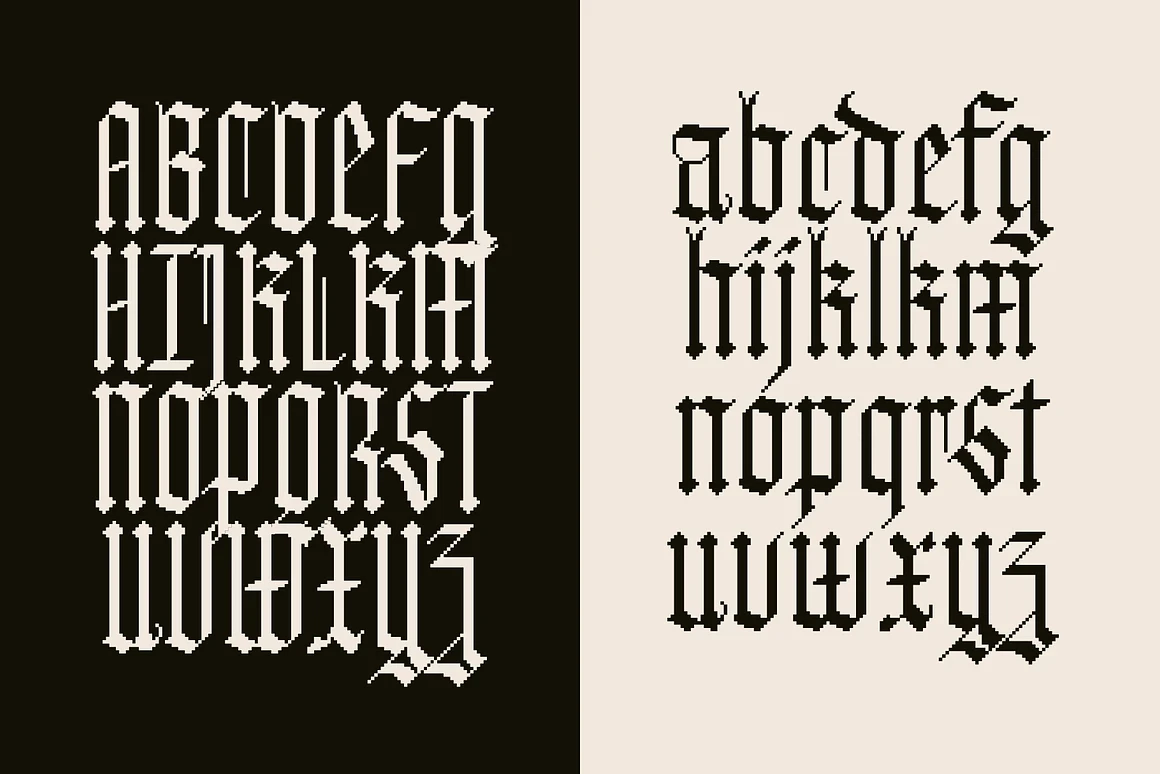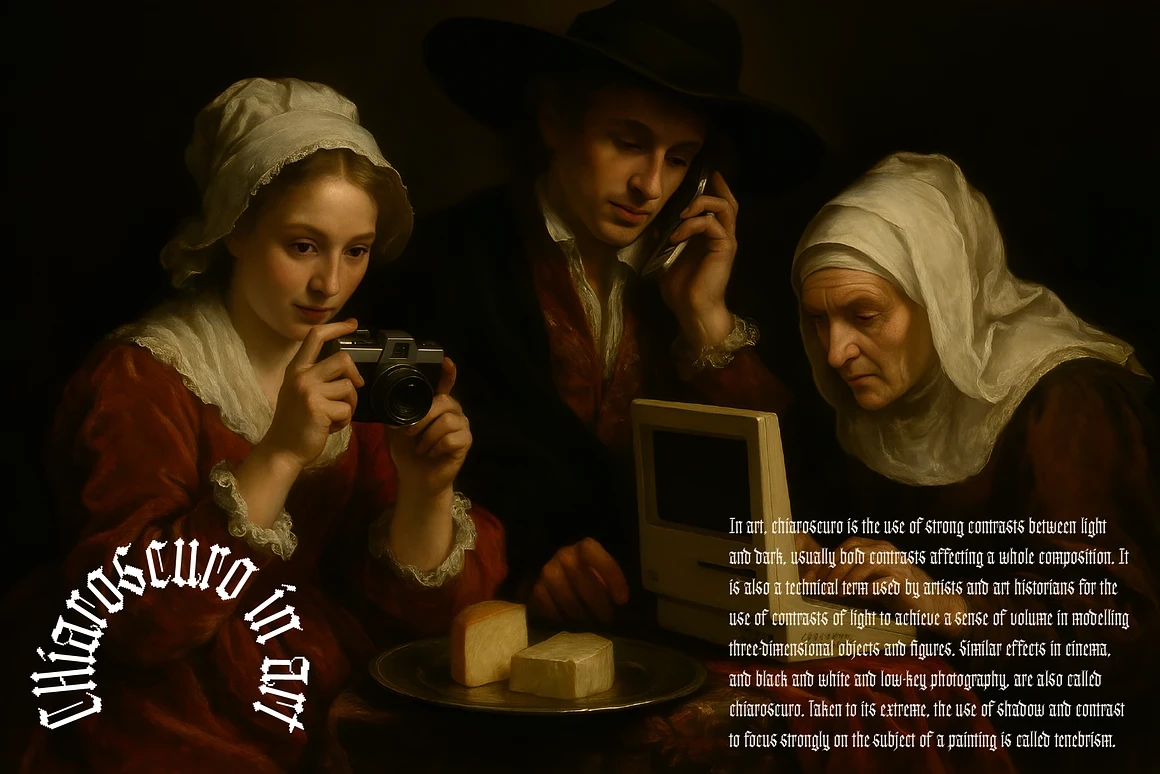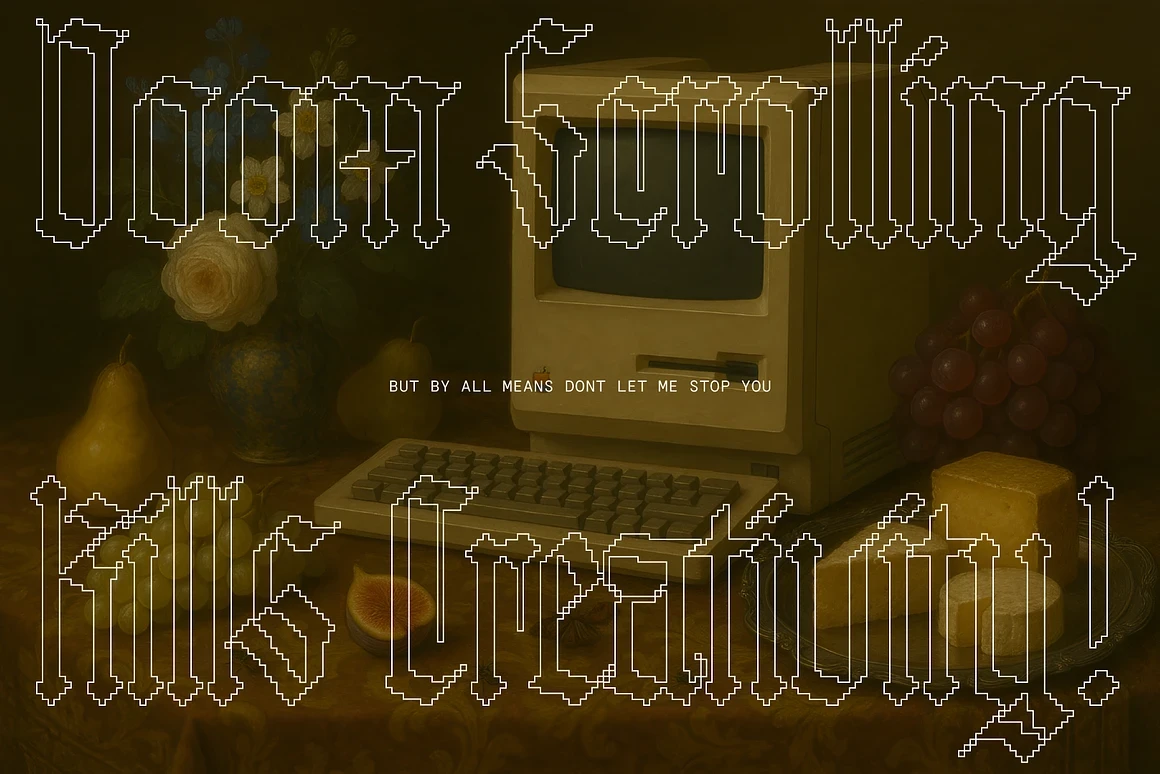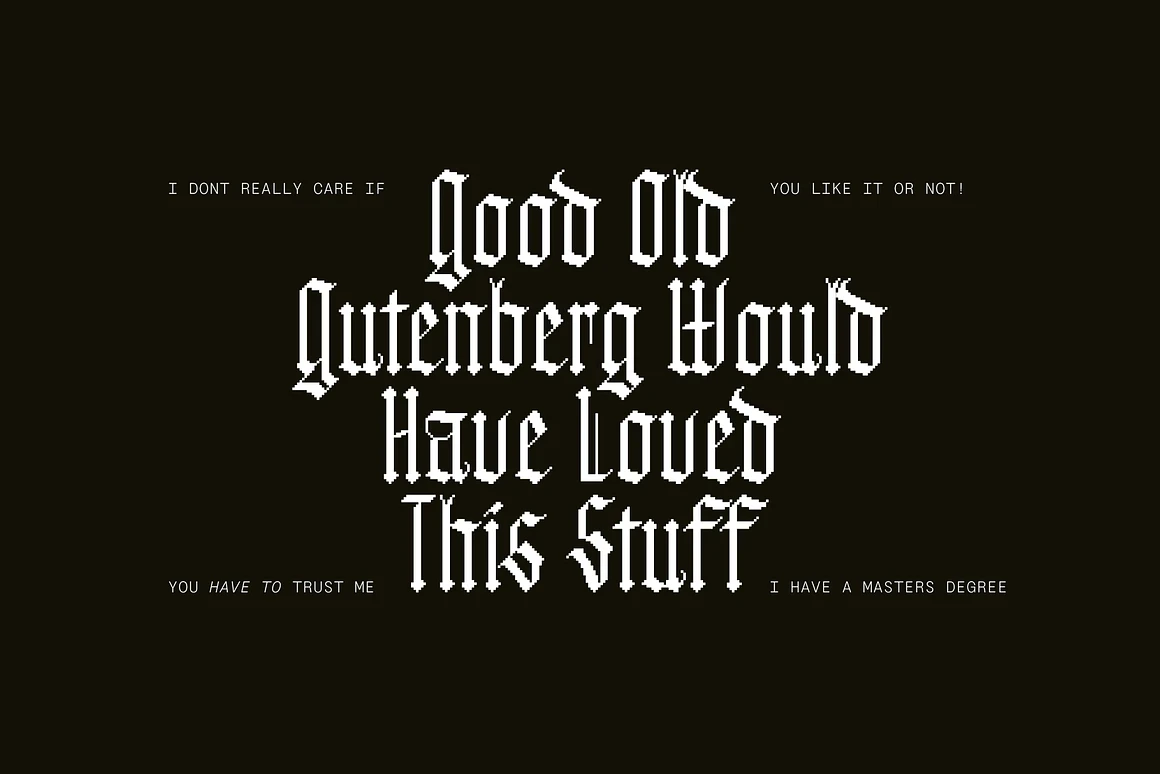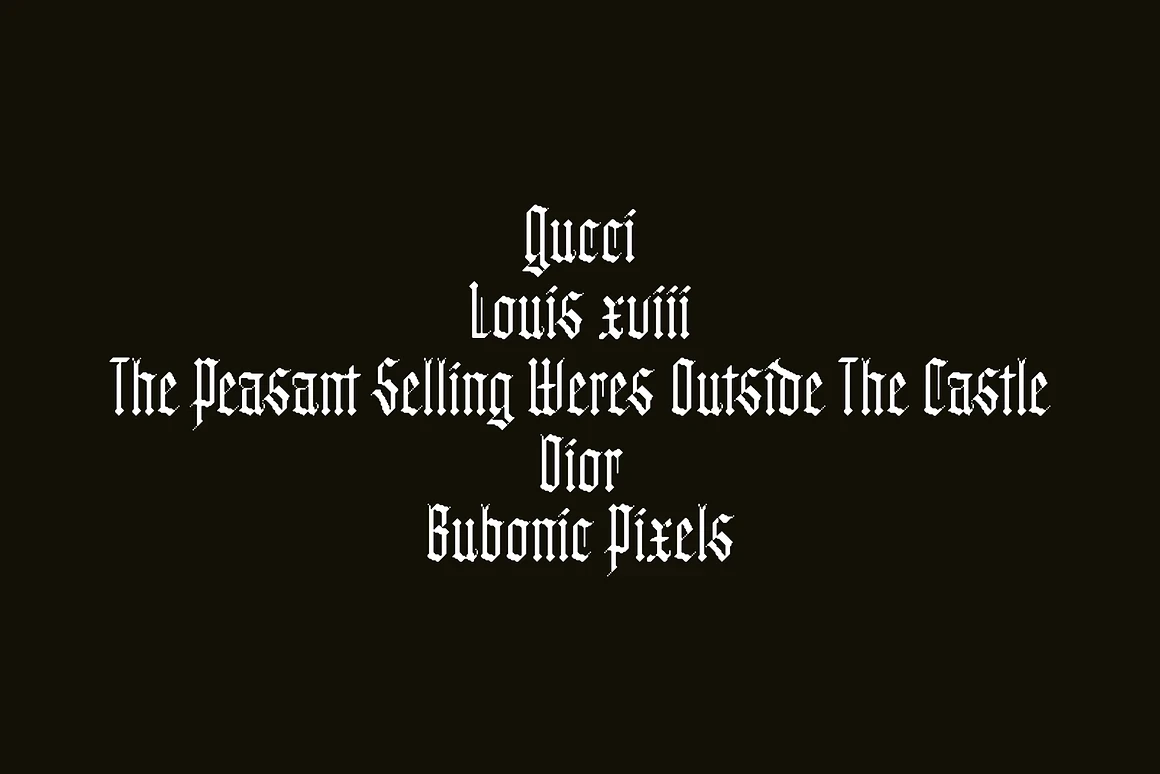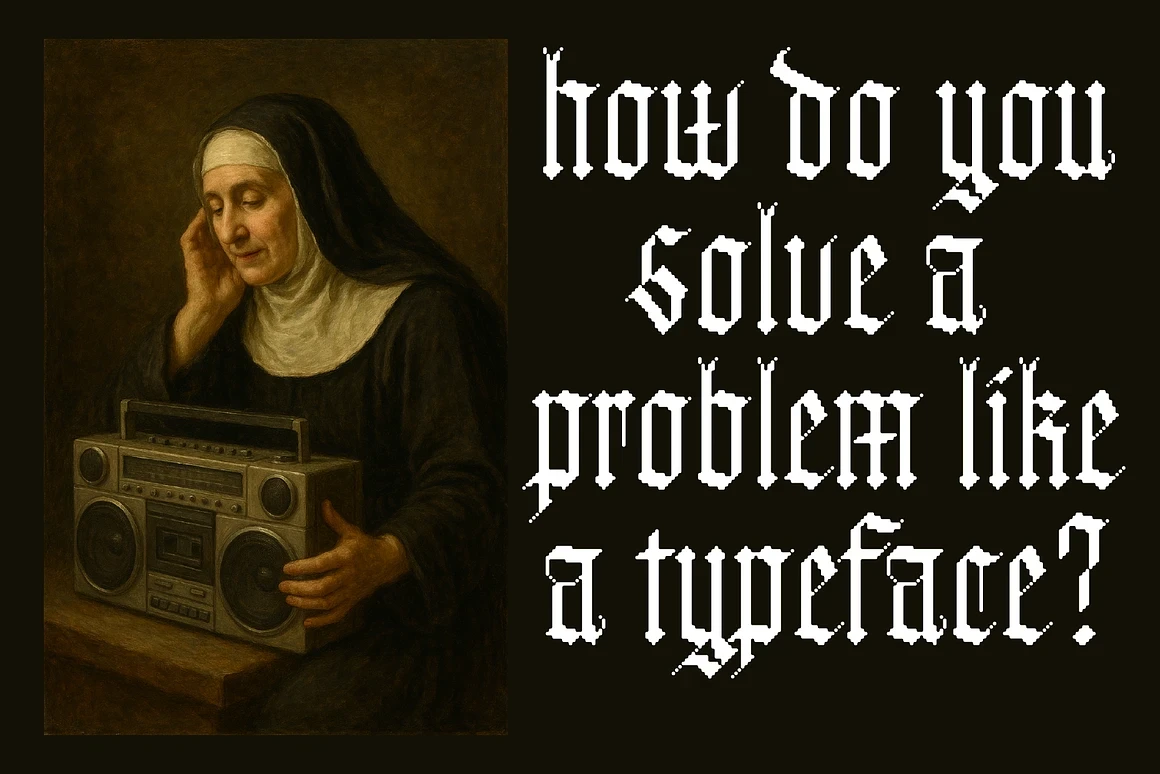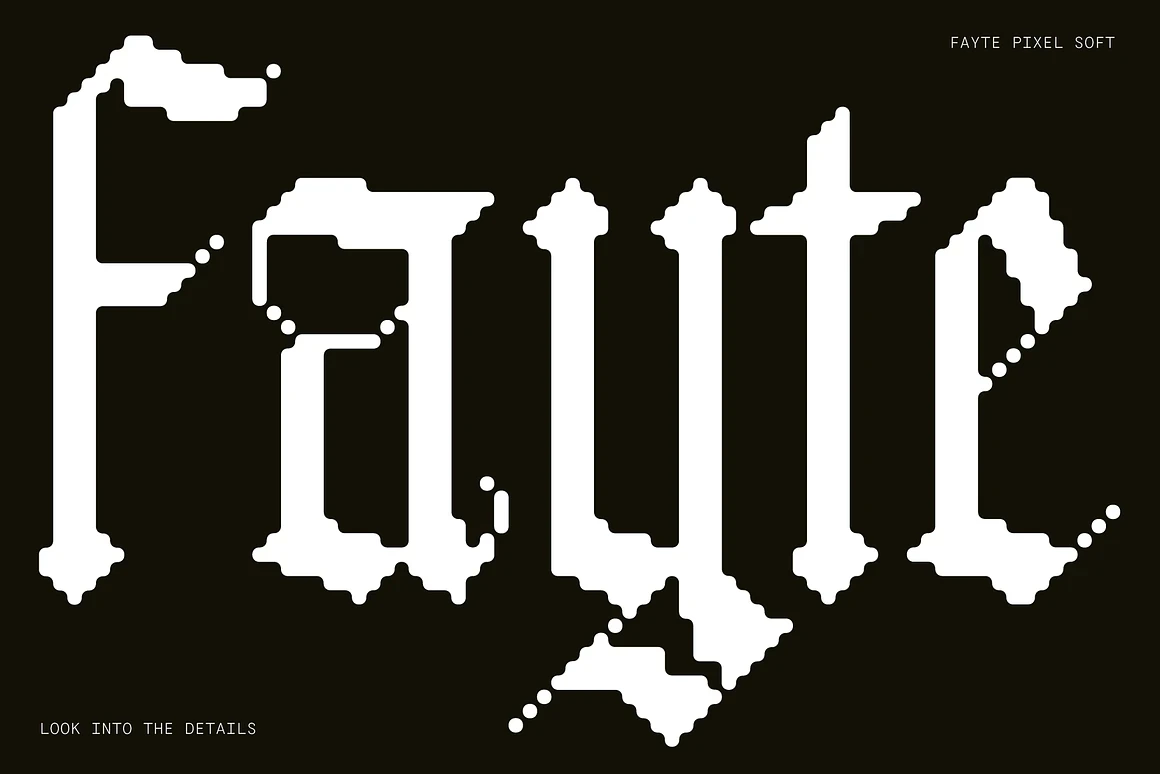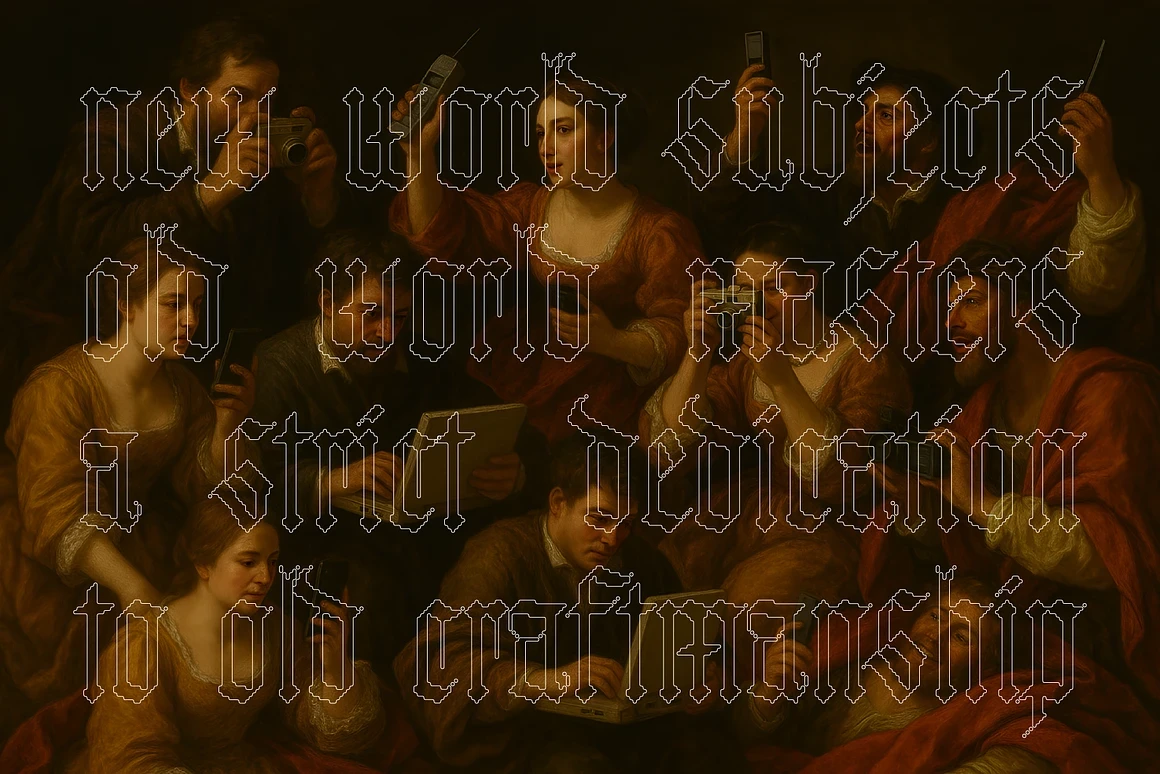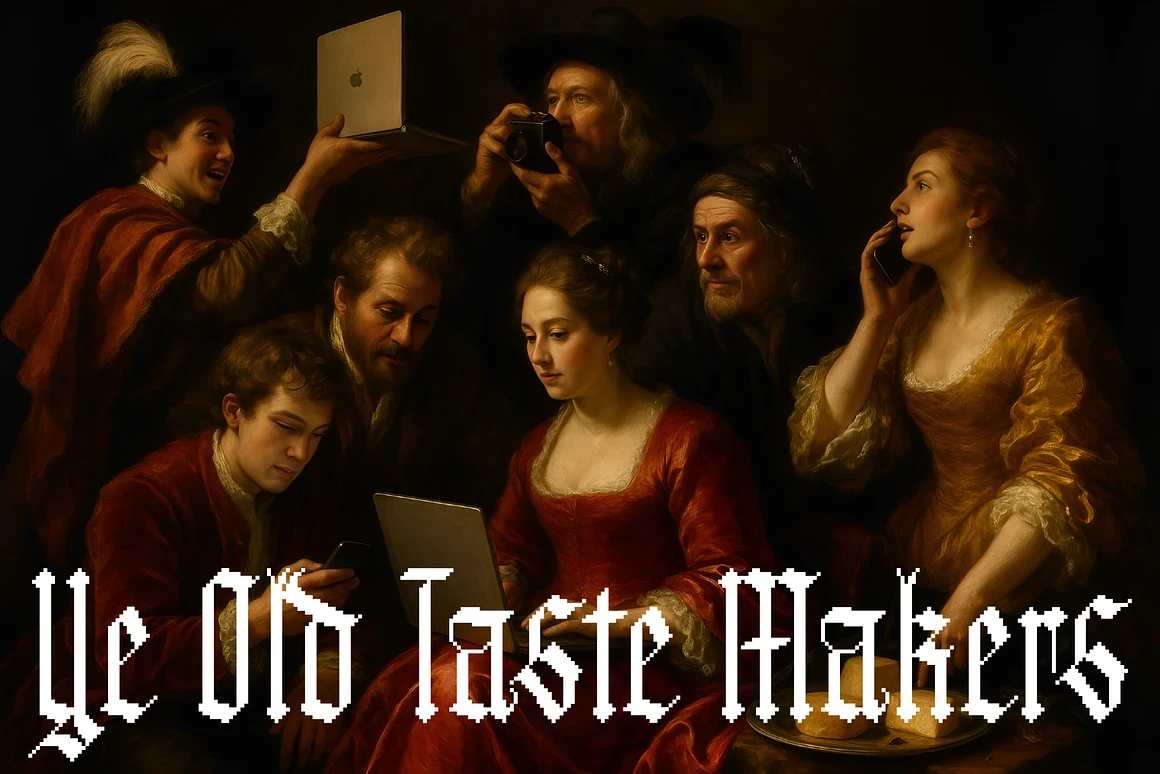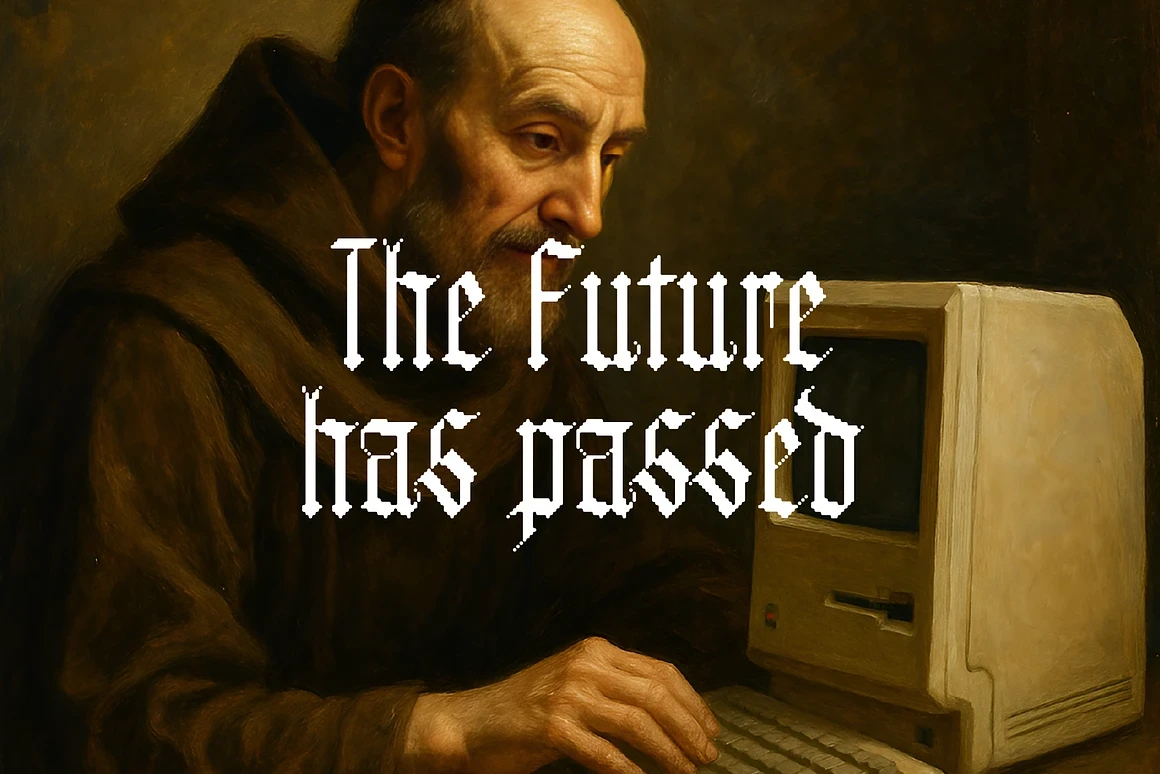
Quả thực, hãy chiêm ngưỡng bộ chữ cao quý này, được tạo nên từ nghệ thuật điểm ảnh, mang phong cách Blackletter, nhưng lại được tôi luyện bởi tinh thần cổ điển và sự tinh xảo của thời đại mới. Nó xuất hiện với hai kiểu dáng tuyệt đẹp: Hard, sắc bén như lưỡi kiếm được tôi luyện của hiệp sĩ, và Soft, mượt mà như tấm da dê mịn màng dưới ngọn bút lông của bạn. Trong mỗi ký tự đều vang vọng tiếng vọng kiên định của người viết kinh trong tu viện và biểu ngữ quầy hàng ngoài chợ, nhưng lại được khoác lên mình lớp áo choàng của khối vuông và retro. Cho những lời tuyên bố, cuộn giấy và trang trí các cõi kỹ thuật số, phông chữ này đứng như một cây cầu giữa sự hiện đại của điểm ảnh và bàn tay thần thánh của thời cổ đại.